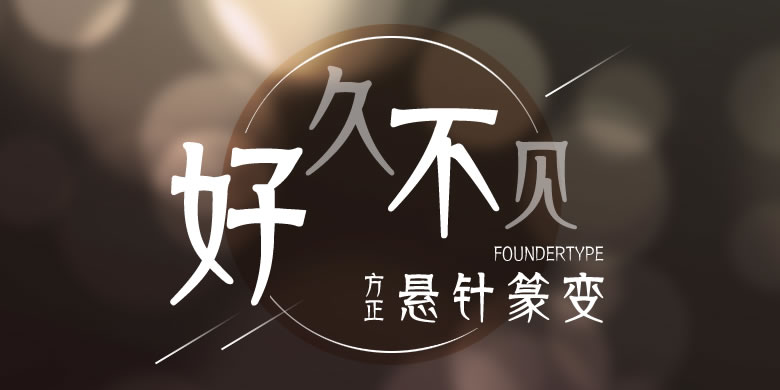
方正悬针篆变
方正悬针篆变的创意源于三国东吴皇象所书的《天发神谶碑》。这款字体的字形保留了篆书悬垂、对称等规律,并将隶书与楷书的笔画特征融为一体,实为三种书体的统一。整体字形修长,结构上密下疏,起笔见方,收笔尖锐,如钢针下悬。方正悬针篆变将传统书法艺术融入现代字形之中,风格复古,装饰性强,适用于历史题材类的宣传设计,以及武侠类的影视、动漫和游戏。